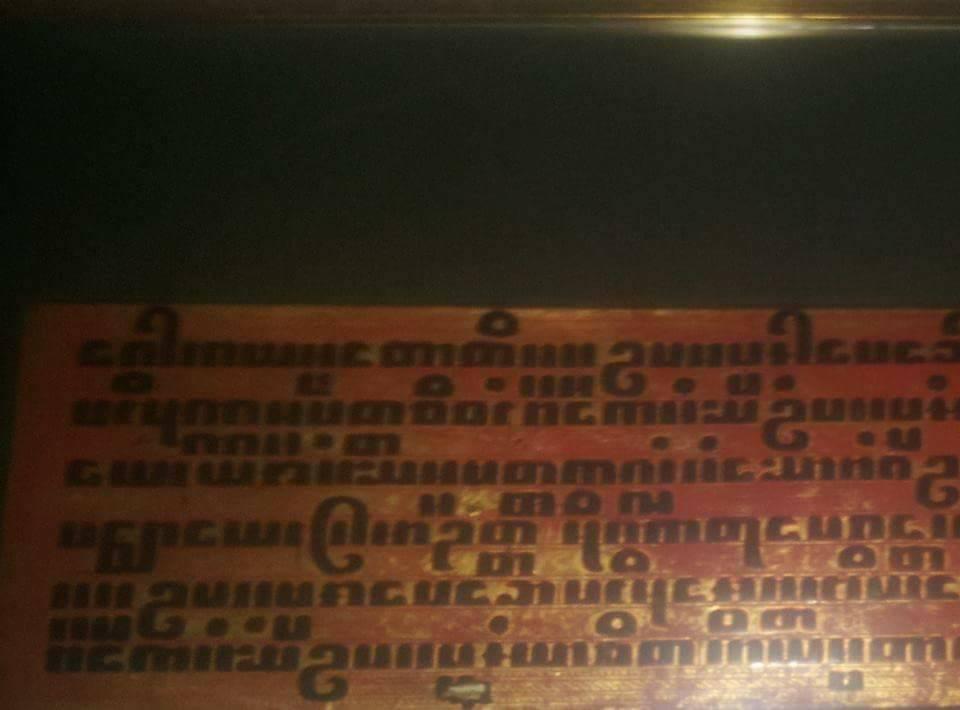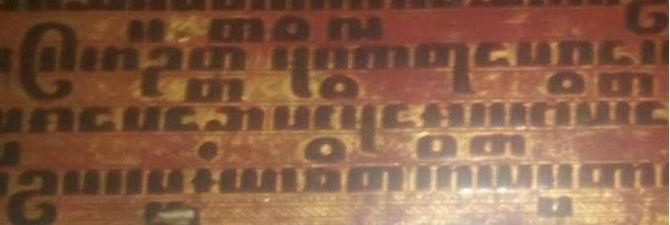
Hier nochmal die Komplettere version!!Der Buchstabe unten taucht ihm ihren vorschlag nicht auf deswegen frage ich^^
Falls es wirklich eine südostasiatische Schrift sein sollte, müsste man dir das z. B. hier: https://www.aai.uni-hamburg.de/soa/ sagen können.
Mir fiel das aber spontan ein, weil ich vor einer Weile parallel zu einem TV-Beitrag über eine Bahnstrecke dort auf Google Maps, OSM und Wikipedia zum Thema rumgestöbert habe und mir das Schriftbild im Kopf hängen blieb.
Armenisch hätte ich bei Misserfolg evtl. als nächstes geprüft ;-)
Wenn ich das aber vergleiche, ist armenisch "zweidimensionaler", während Dein Bsp. "dreidimensionaler" aussieht, wo also über/unter den "vollen" Zeilen noch relativ viele einzelne Zeichen / Anhängsel hängen, was besser zum birmanischen zu passen scheint, auch wegen der Vokalzeichen  & Co.
Das eine hervorgehobene Zeichen kommt im armenischen aber auch nicht vor, könnte aber als gestalterische Variante durchaus zu einigen birmanischen passen.
Habe nach dem Antworten gestern spät abends noch festgestellt, dass
https://de.wikipedia.org/wiki/Birmanische_Schrift
der bessere Link gewesen wäre ... Unten wird auch auf
https://commons.wikimedia.org/wiki/Category:Burmese_script?uselang=de
verlinkt mit Bild-Bsp.
Aber sicher bin ich mir absolut nicht, nur eine Vermutung. VIelleicht suche ich nachher mal den Schriftatlas raus ...
Zur Variationsbreite des Birmanischen siehe auch
https://commons.wikimedia.org/wiki/File:Das_Buch_der_Schrift_(Faulmann)_161.jpg
So ähnlich könnte es bei jeder Schrift werden, es bleibt also knifflig ... ;-)
Das Buch ist von 1880 und wohl komplett gescannt, womöglich findet sich da auch noch eine andere passende Schrift drin ...
https://commons.wikimedia.org/wiki/File:Das_Buch_der_Schrift_(Faulmann)_012.jpg
Mein Stöbern im "Bildatlas der Sprachen" brachte leider keine weitere Erkenntnis ...